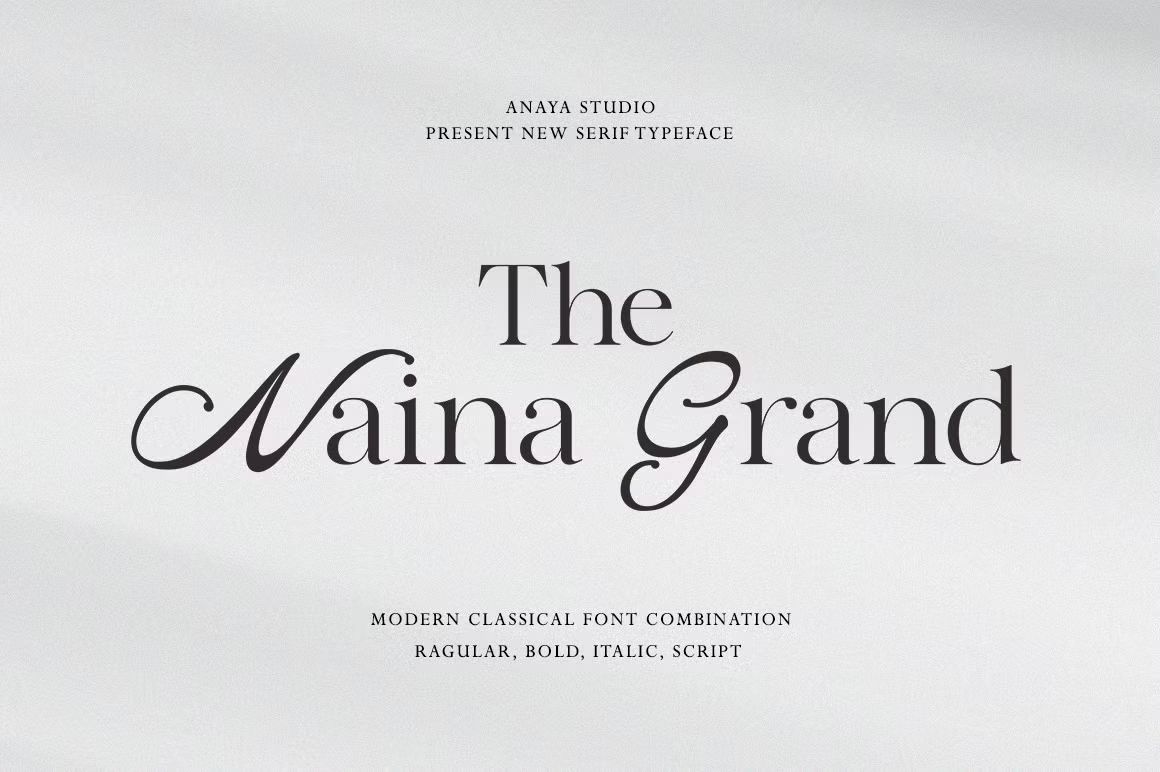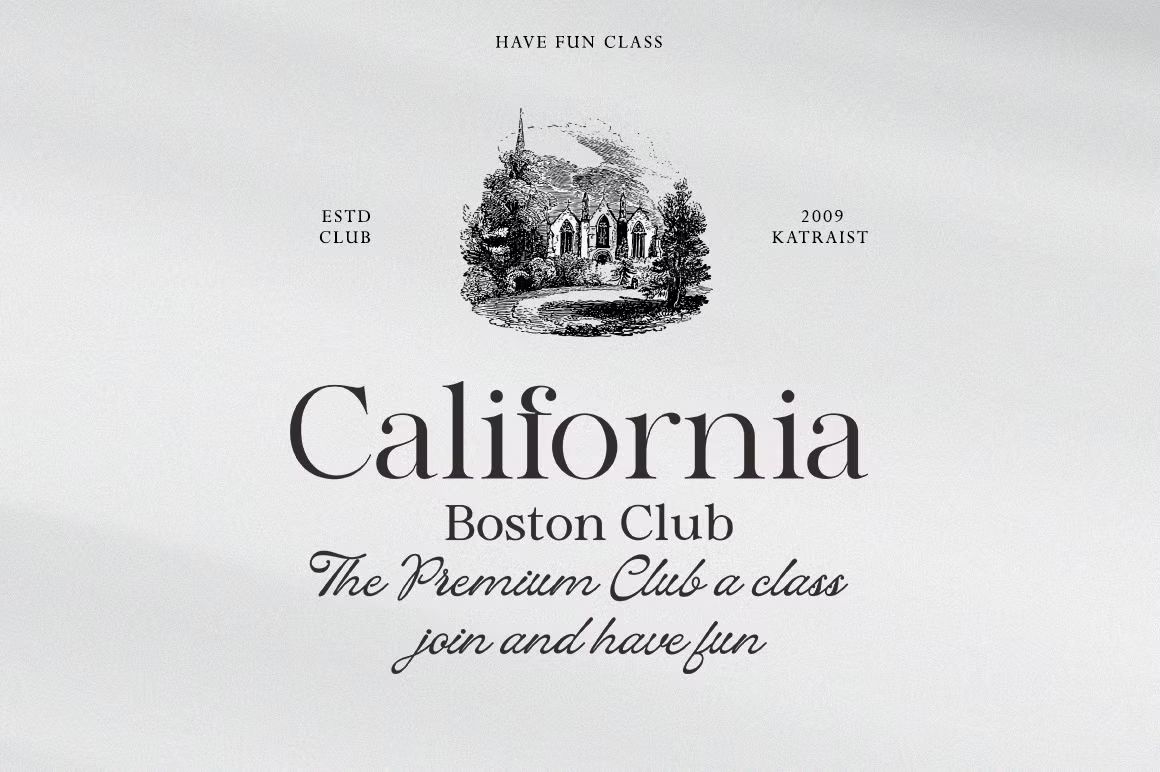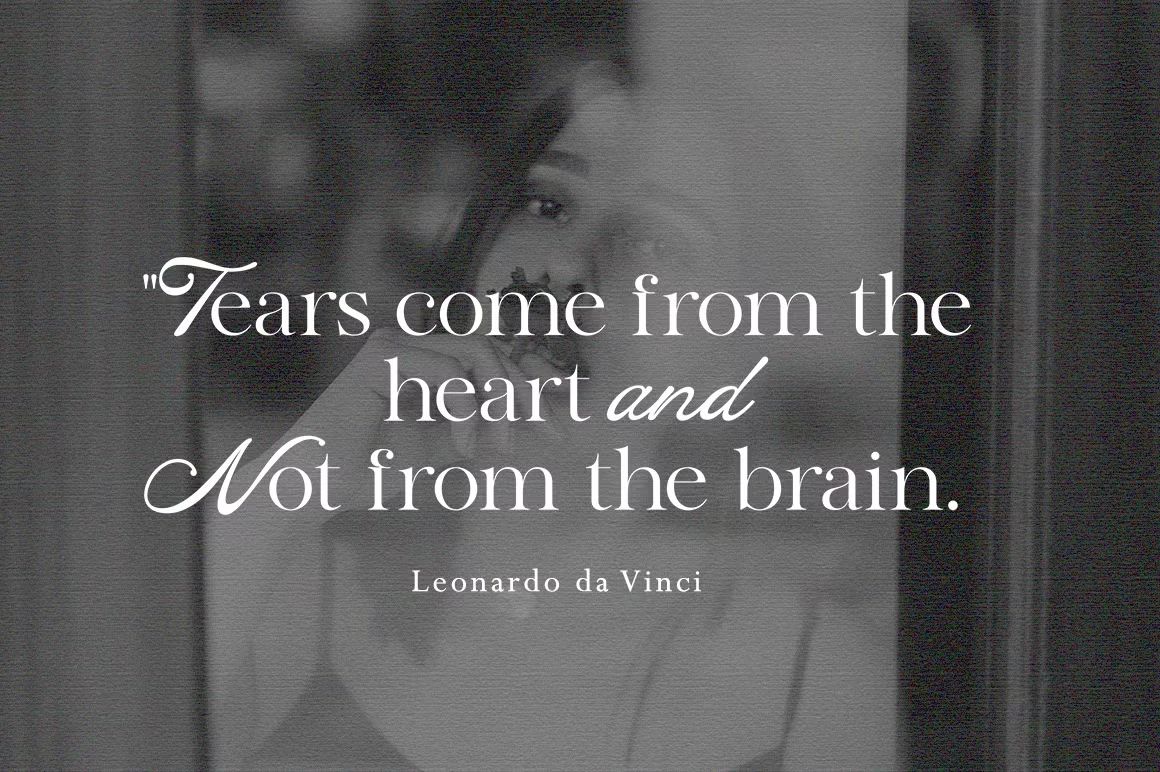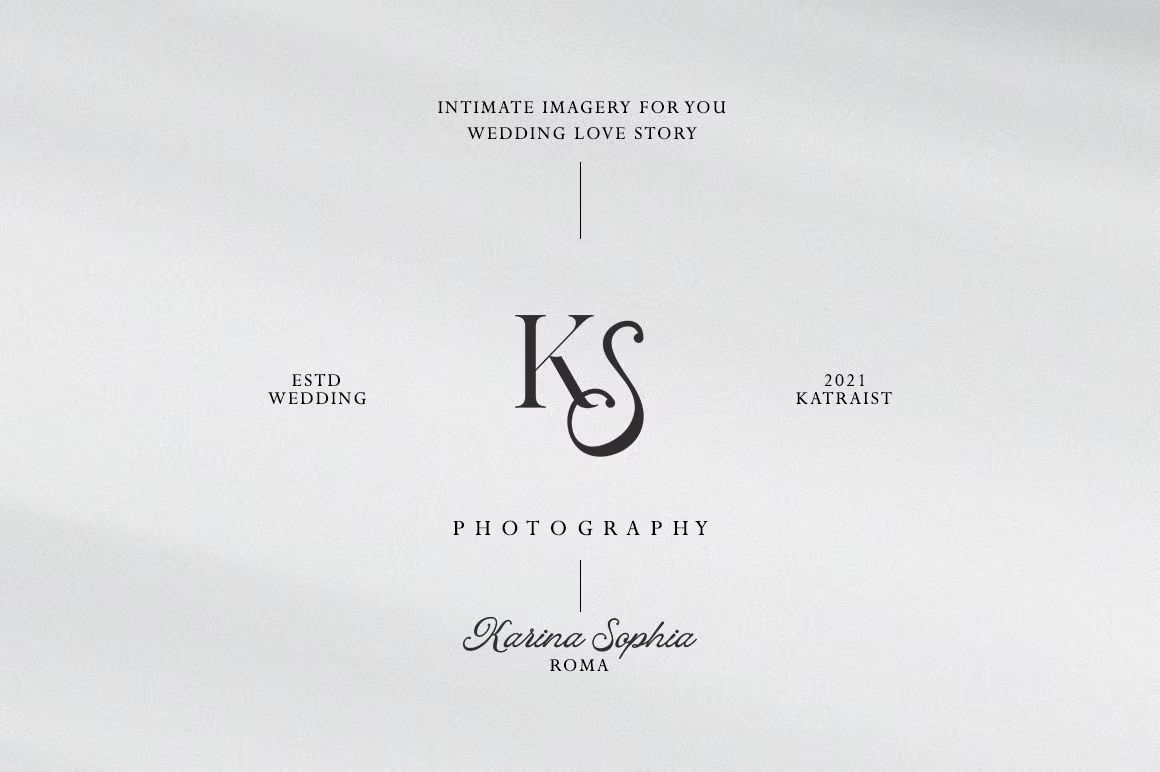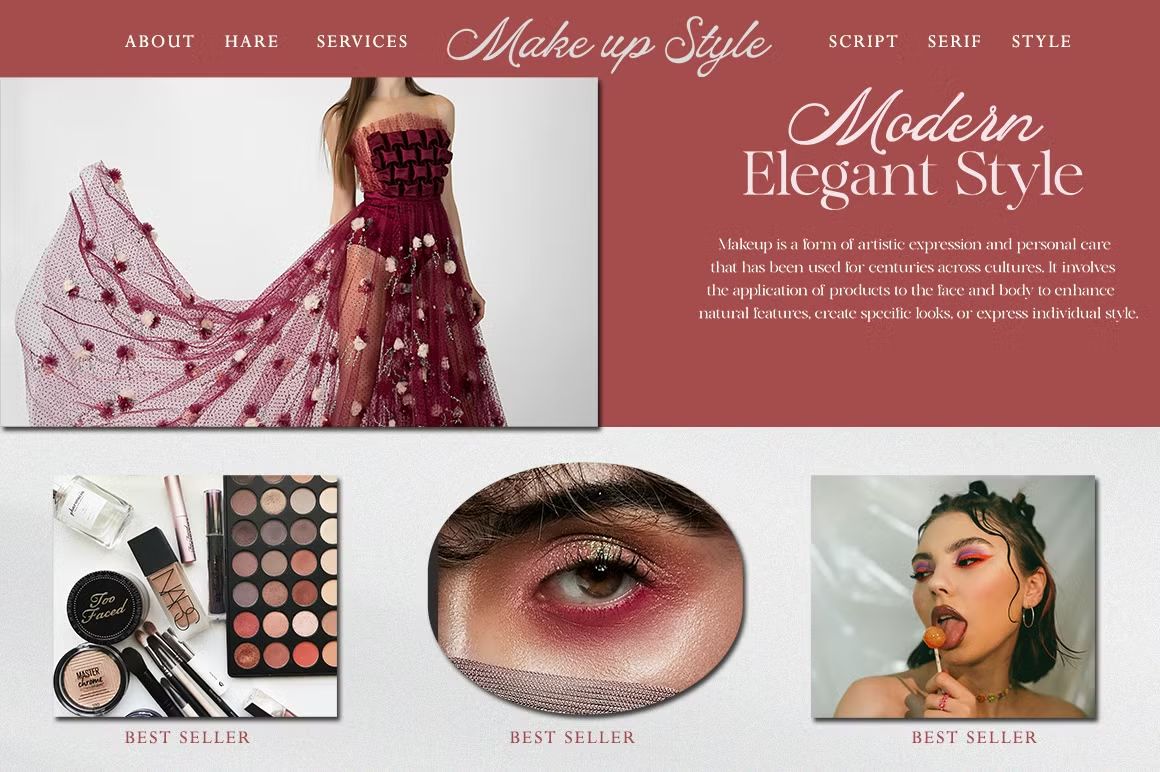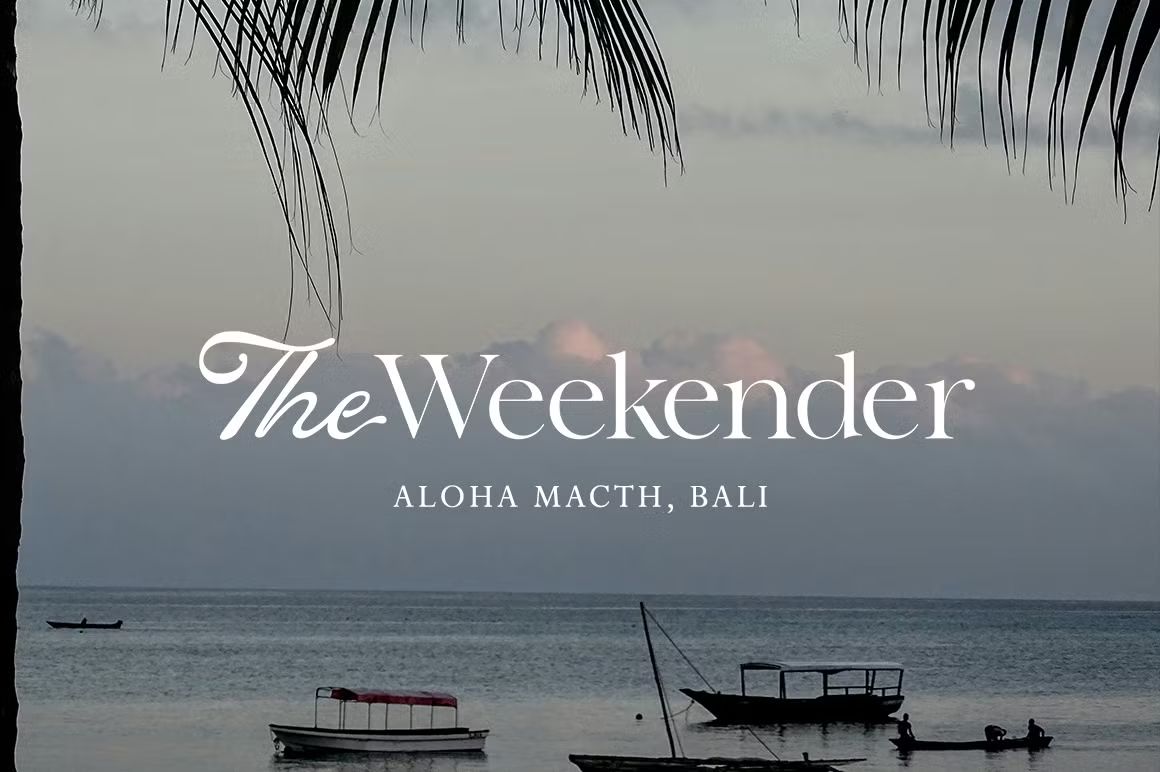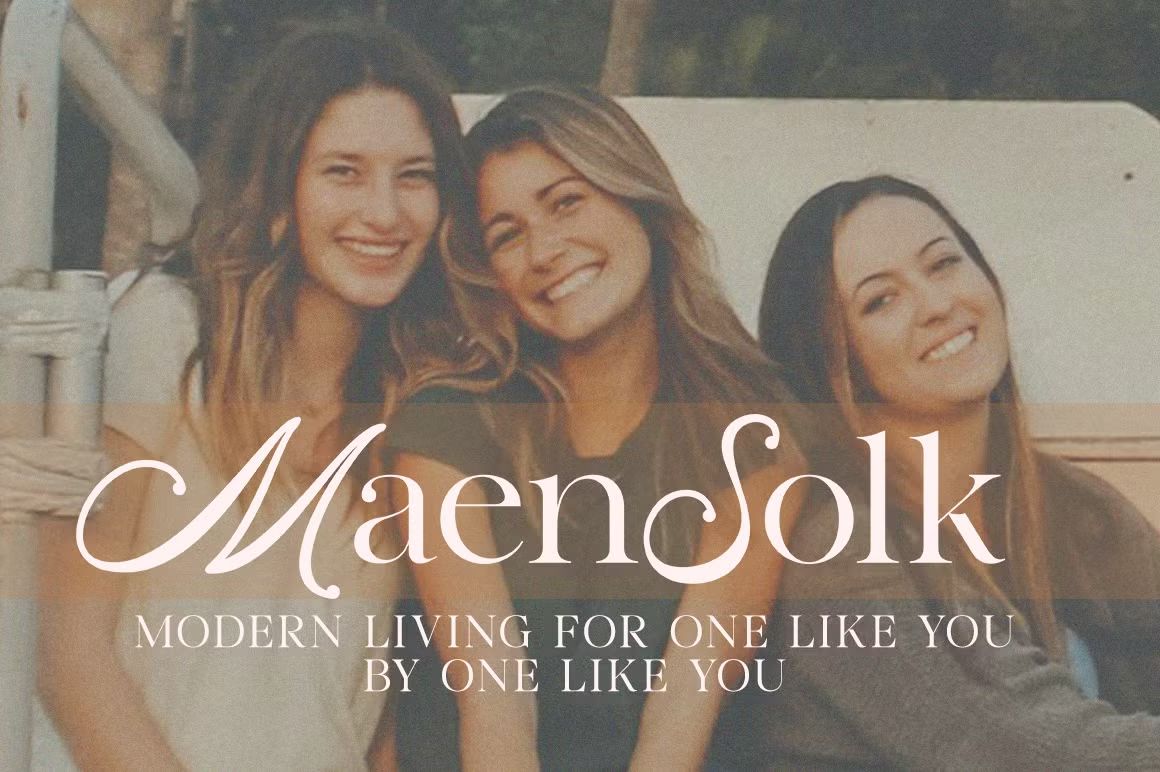
The Naina Grand – Sans Serif Font
The Naina Grand adalah font sans serif elegan dan modern, cocok untuk branding premium dan desain profesional. Format OTF/TTF/WOFF, siap digunakan.
The Naina Grand adalah font sans serif modern dengan tampilan elegan dan berkelas. Menampilkan bentuk huruf ramping, proporsi seimbang, dan detail halus, font ini sangat cocok untuk branding premium, desain fashion, editorial, kemasan mewah, dan presentasi profesional. The Naina Grand menghadirkan kesan eksklusif dan minimalis dalam satu paket tipografi yang elegan.
• Sans serif bergaya elegan dan profesional
• Ideal untuk branding mewah, editorial, dan desain fashion